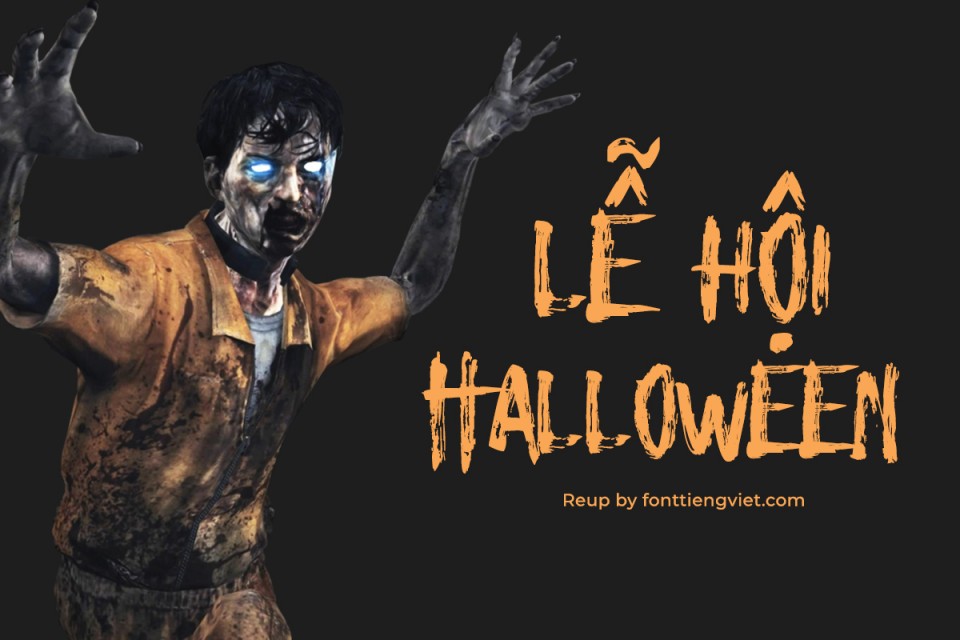
Giới thiệu về Font việt hóa LNTH Zombies
Trong thế giới đồ họa hiện đại, việc lựa chọn Font Chữ phù hợp đóng vai trò then chốt giúp truyền tải thông điệp hiệu quả. Font việt hóa LNTH Zombies là một bộ phông đặc biệt, mang phong cách rùng rợn, cá tính và đầy sức sống. Đây là lựa chọn lý tưởng cho các bạn học sinh, sinh viên muốn tạo nên những bài thuyết trình ấn tượng hoặc các ấn phẩm truyền thông độc đáo trong môi trường học đường. Bộ font này đã được tối ưu hóa tiếng Việt hoàn chỉnh, giúp người dùng không còn lo lắng về lỗi hiển thị dấu câu hay các ký tự đặc biệt khi soạn thảo văn bản trên máy tính.
Đặc điểm nổi bật của Font việt hóa LNTH Zombies
Phong cách thiết kế độc đáo
Font việt hóa LNTH Zombies sở hữu những đường nét thô ráp, mô phỏng hình ảnh các thây ma trong điện ảnh, tạo cảm giác kịch tính và mạnh mẽ. Tuy mang hơi hướng kinh dị, nhưng nhờ sự tinh chỉnh khéo léo, bộ font vẫn giữ được độ dễ đọc cần thiết. Điều này rất quan trọng khi ứng dụng vào các tiêu đề sách, bìa báo tường hoặc các dự án nghệ thuật của nhà trường. Sự kết hợp giữa tính nghệ thuật và tính ứng dụng giúp bộ font này trở nên khác biệt so với các phông chữ truyền thống thông thường.
Tính ứng dụng đa dạng
Bên cạnh mục đích giải trí, Font việt hóa LNTH Zombies còn được sử dụng rộng rãi trong thiết kế áo lớp, logo câu lạc bộ hoặc các poster sự kiện Halloween tại trường học. Khả năng tương thích tốt với nhiều phần mềm thiết kế giúp quá trình sáng tạo trở nên mượt mà hơn.
Kết luận và cách sử dụng font hiệu quả
Sử dụng Font việt hóa LNTH Zombies đúng cách sẽ giúp sản phẩm của bạn trở nên chuyên nghiệp và thu hút hơn. Hãy luôn lưu ý cân bằng giữa kiểu chữ trang trí và nội dung để người xem dễ dàng tiếp nhận thông tin nhất. Chúc các bạn có những trải nghiệm tuyệt vời với Font Miễn Phí, Font Việt Hóa, Font việt hóa LNTH Zombies trong các dự án sáng tạo sắp tới của mình.